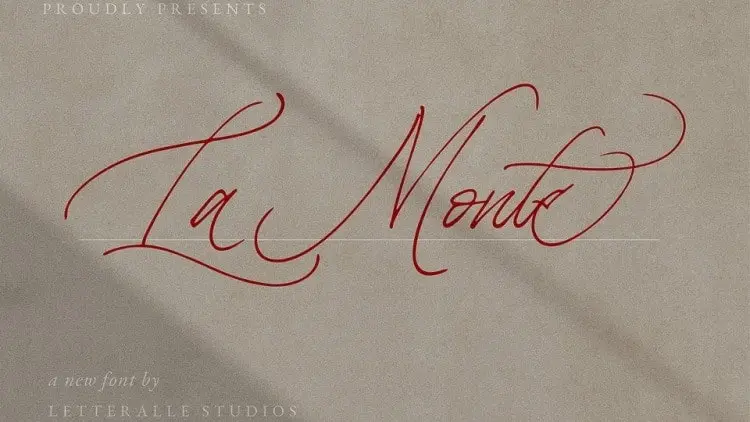
A La Monte Script é uma fonte que se apresenta com uma mistura única entre tipografia moderna clássica e detalhes sofisticados contemporâneos. Com toques naturais e detalhes meticulosamente criados, esta fonte traz um ar elegante que certamente deixará suas criações de design em outro patamar. La Monte Script é perfeita para os profissionais de design gráfico que buscam uma fonte de escrita artesanal moderna. Com várias alternativas para cada letra, essa fonte mantém seu encanto e estilo único, tornando-a irresistivelmente atrativa. Além disso, a La Monte Script se destaca por oferecer suporte para múltiplas línguas, tornando-a uma opção versátil para projetos internacionais. Ideal tanto para designers de logotipos quanto para aqueles que desejam um toque sofisticado em texturas ou menus, a La Monte Script é certamente um investimento valioso na sua coleção de fontes.